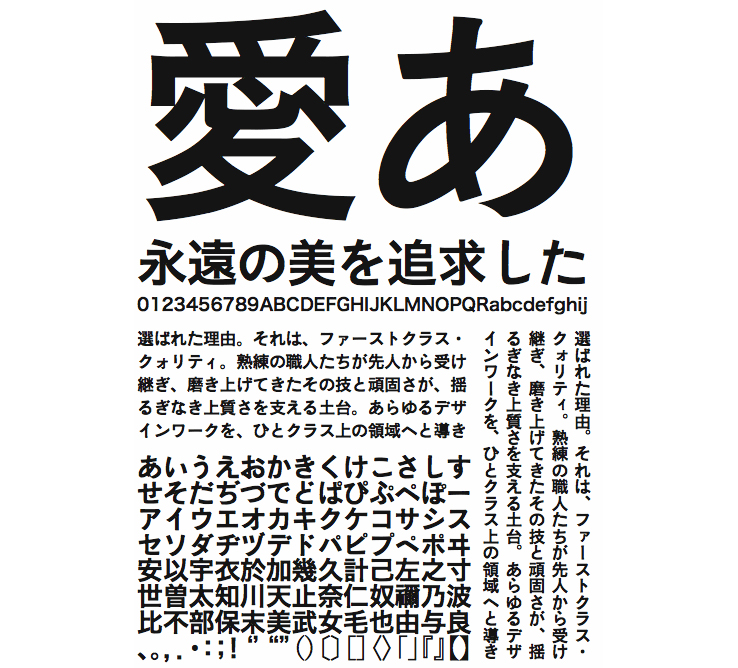
【ヒラギノ角ゴ オールド】キャッチフレーズから小見出しに至るまで、強調したい文章を表情豊かに組めるよう、「ヒラギノ角ゴ」の漢字に、東京築地活版製造所の名作ゴシックを飜刻した「游築初号ゴシックかな」をあわせました。強さ、やさしさ、厳しさ、ユーモラスさといった様々な表情を備えたダイナミックさが持ち味です。